空間のなかで生きる文字
建築家/デザイナー 寺田 尚樹氏
2015年3月、南池袋に誕生した超高層ビル「としまエコミューゼタウン」は、区役所と超高層マンションを一体化させた日本初のプロジェクトです。この施設内のいたるところで目にすることができ、人を導く役割を果たしているのが、さまざまな素材を用いたサインパネル。そこにはAXIS Fontが使われています。
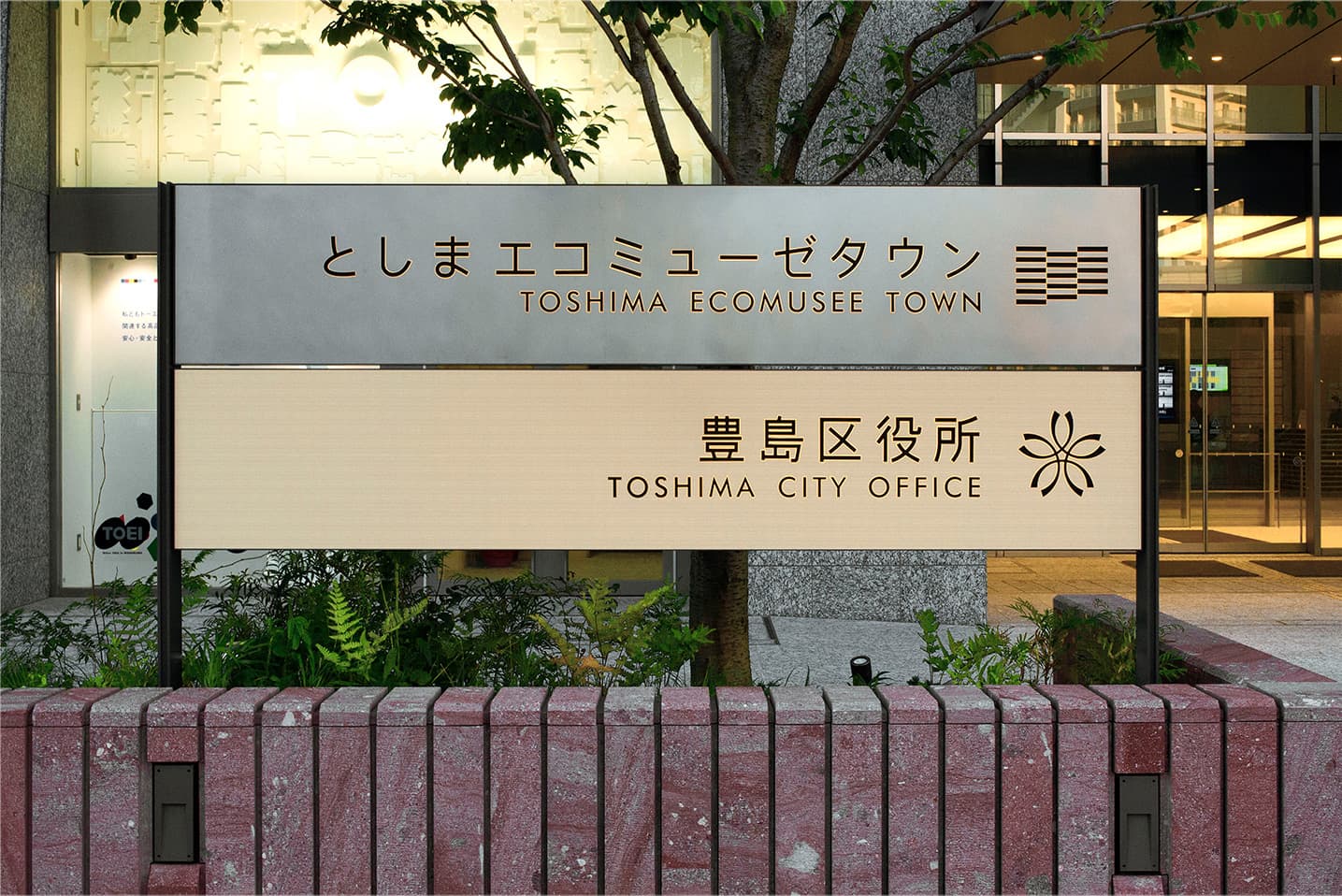
「としまエコミューゼタウン」のサイン計画を手がけたテラダデザイン一級建築士事務所・主幹の寺田尚樹氏は、グッドデザイン賞審査員、武蔵野美術大学非常勤講師も務め、建築設計のみならず、アイスクリームスプーン「15.0%」をはじめとするプロダクトデザイン、紙で作る1/100スケールの模型の世界「テラダモケイ」など、幅広い分野を活動の場としています。
「僕はロンドンのAAスクール(Architectural Association School of Architecture)という建築学校で学びました。日本では建築家は建物を考える人というイメージですが、ヨーロッパでは立体物を設計する人全般がアーキテクトと呼ばれます。建築家なら、いろんなものを作り出すことができる。そういう人になりたくて、海外の学校を選んだのです。ですから現在の仕事でも、建築だけでなく、空間に関わるプロダクトのデザインが大きなウエイトを占めています。そして僕にとってサインデザインは、そのようなインテリアプロダクトの延長線上にあります。たとえば壁掛け時計をデザインするときには、それが置かれる場所の天井の高さなど、各種の空間的要素をしっかりとイメージすることが重要となりますが、サインも同様です。建築、インテリアプロダクト、サインは、すべてつながっているのです」(寺田氏)
「としまエコミューゼタウン」プロジェクトでは、設計を日本設計が、外観のデザイン監修を隈研吾建築都市設計事務所が担当。建物の外装は、エコヴェールと呼ばれる植栽パネルや太陽光パネルなどで覆われたデザインです。日本設計からサイン計画を一任された寺田氏らは、エコヴェールと同じ縦横比のサインパネルを採用し、パネルの素材を区役所=木目、店舗=ガラス、共用部=ステンレス、集合住宅=ブラックステンレスとするサインシステムを立案しました。
「依頼を受けたときに『サイン計画は建築家に頼みたかった』と言われたのがうれしかったですね。その期待にどう応えようかと考えて、サインを建築の仕上げ素材の一部であるようにデザインするというアイデアに行き着きました。このシステムでは、ステンレス、木目、ガラスなどの素材のサインパネルが床や壁などに配置され、そこに文字が刻まれることとなりますが、クセのある書体だと背景の素材によって印象が変わってしまいます。そこで、多様な素材に対して常にニュートラルな関係性を保てる書体という観点から、AXIS Fontを選びました。そしてもうひとつ、同じ看板のなかで要素の重み付けを変えたい場合、複数のウエイトを混在させても統一感が損なわれないという点でも、AXIS Fontが最適でした。
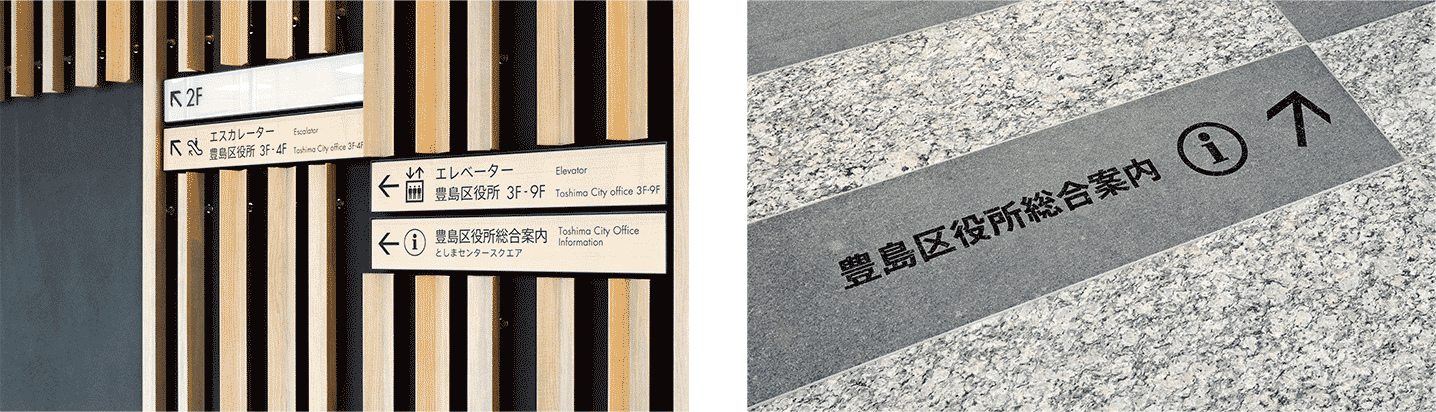
作品だけでなく、プレゼン資料などにもAXIS Fontを利用しているという寺田氏は、とくに細いウエイトと太いウエイトの組み合わせがお気に入りだそうです。「AXIS Fontは凝った調整をしなくてもきれいに組める、僕にとってはデフォルトのフォントです。細めのものをメインで使って太いものをアクセントにする、そういう見せ方がとても効果的です。また、TP明朝は他の明朝体にはない現代的な感覚が魅力なので、これまで無意識にゴシックを選んでいたようなシーンで使ってみたいですね」